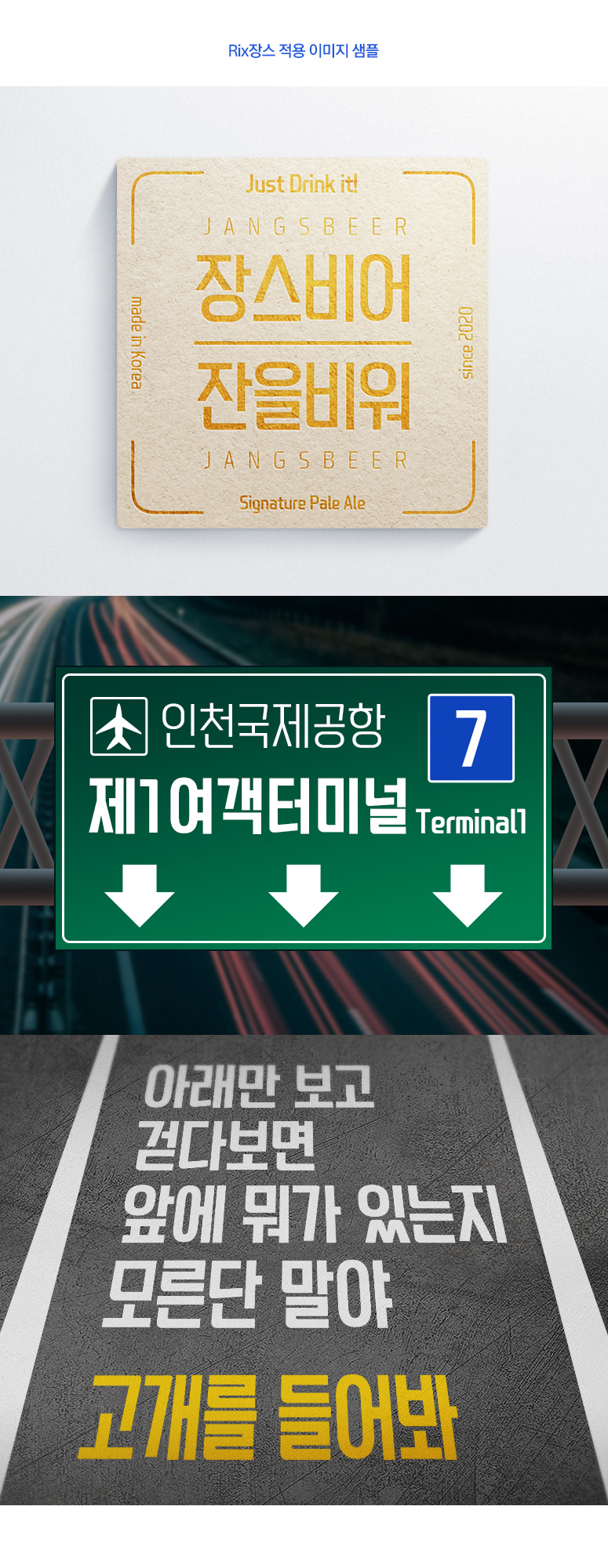
Rix장스는 폭이 좁고 꽉 찬 모듈을 컨셉으로 제작된 폰트로 간결한 직선 형태와 부드러운 라운드 스킨을 적용하였고, 글자의 폭이 좁아져 불안정한 형태 및 굵기에 가변을 사용하여 글자를 제대로 표현할 수 있도록 설계하였습니다. 좁은 곳에 많은 텍스트를 사용하거나 눈에 띄는 타이틀용으로 사용하기에 적합합니다.